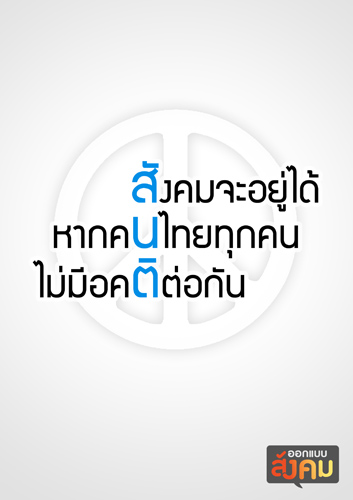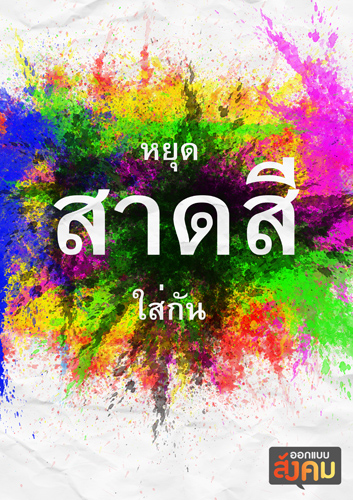
โจทย์ประจำยุคสมัยเรา:ออกแบบสังคม
ชื่อผลงาน : ลืมถิ่นเกิด
แนวคิด : บางครั้งเรานึกถึงแต่ประโยชน์ส่วนตน จนลืมส่วนรวม
โดย : อนุชา เธียรศิริพิพัฒน์
ทำอะไรอยู่ในสังคมไทย : เตรียมตัวเผชิญชีวิตนอกรั้วมหาลัย
คติพจน์ : อย่ามัวคิด อย่ามัวฝั่น...ตื่นมาทำได้แล้ว, ปัจจุบันสำคัญที่สุด
เขียนสวยมาก แต่เอามาทำเป็นกราฟิกได้ไม่ลงตัวนัก คือรูปวาดมันสวย
มันทำอะไรได้เจ๋งกว่านี้เยอะ วางไทโปธรรมดาด้วย
คนไทยรักกัน (Chill - ขิม)
ชื่อผลงาน : คนไทยใจชิลๆ
แนวคิด : เย็นไว้ก่อน ชิลไว้นะเธอว์
โดย : aom (aomjai.blogspot.com)
ทำอะไรอยู่ในสังคมไทย : อาจารย์มหา'ลัย ที่ชอบตีขิม
คติพจน์ : อยากเห็นคนไทยรักกัน
ว่าแต่ ชอบไอ้สันติสุขอยู่คู่ประเทศไทยจังเลย แต่มันคงต้อง
เอามาทำอะไรอีกมาก ผมว่าถ้าทำอันนี้จริง คนแย่งหยิบเลยนะ
มันเปรี้ยงเดียวอยู่เลยอะ ขออนุญาตเอาไอเดียคุณฟรีคลับตรงนี้
ไปโปรดัคชั่นใหม่ มีใครมีเวลาฟีเจอริ่งไหมครับ อยากให้มีอันนี้จริงๆ
ทั้งที่คนฮาและไม่คิดอะไรนี่แหละ แต่มันเป็นอันที่ใครๆจำได้ดีที่สุดแล้ว
(อันเก่าคือ 'ฟังมาแล้วคิด คิดแล้วจึงพูด' กับ 'ไทยหลากสี' ครับ แต่ตอนนั้นยังไม่ได้สมัครบอร์ด)
ชื่อ: สันติ
แนวคิด: สังคมจะอยู่ได้หากคนไทยทุกคนไม่มีอคติต่อกัน
โดย: ธนวิชญ์ ประสงค์พษ์ัชัย
ทำอะไรอยู่ในสังคมไทย: นักเรียน
ชื่อ: สาดสี
แนวคิด: ตอนนี้ถ้าใครไม่เห็นด้วยกับเรา แต่ละคนก็จะมองว่าอีกคนเป็นอีกสีไปเลย
โดย: ธนวิชญ์ ประสงค์พษ์ัชัย
ทำอะไรอยู่ในสังคมไทย: นักเรียน
ชื่อ: สามัคคีสีรุ้ง
แนวคิด: รอคอยวันที่กลีบแต่ละสีจะกลับมารวมกัน ให้ความสามัคคีของชาติเบ่งบานขึ้นอีกครั้ง เมื่อสีทุกสีมาผสมกันจะกลายเป็นสีไตรรงค์
โดย: faith99 (Chayot Kiranantawat)
ทำอะไรอยู่ในสังคมไทย: เพิ่งจบ